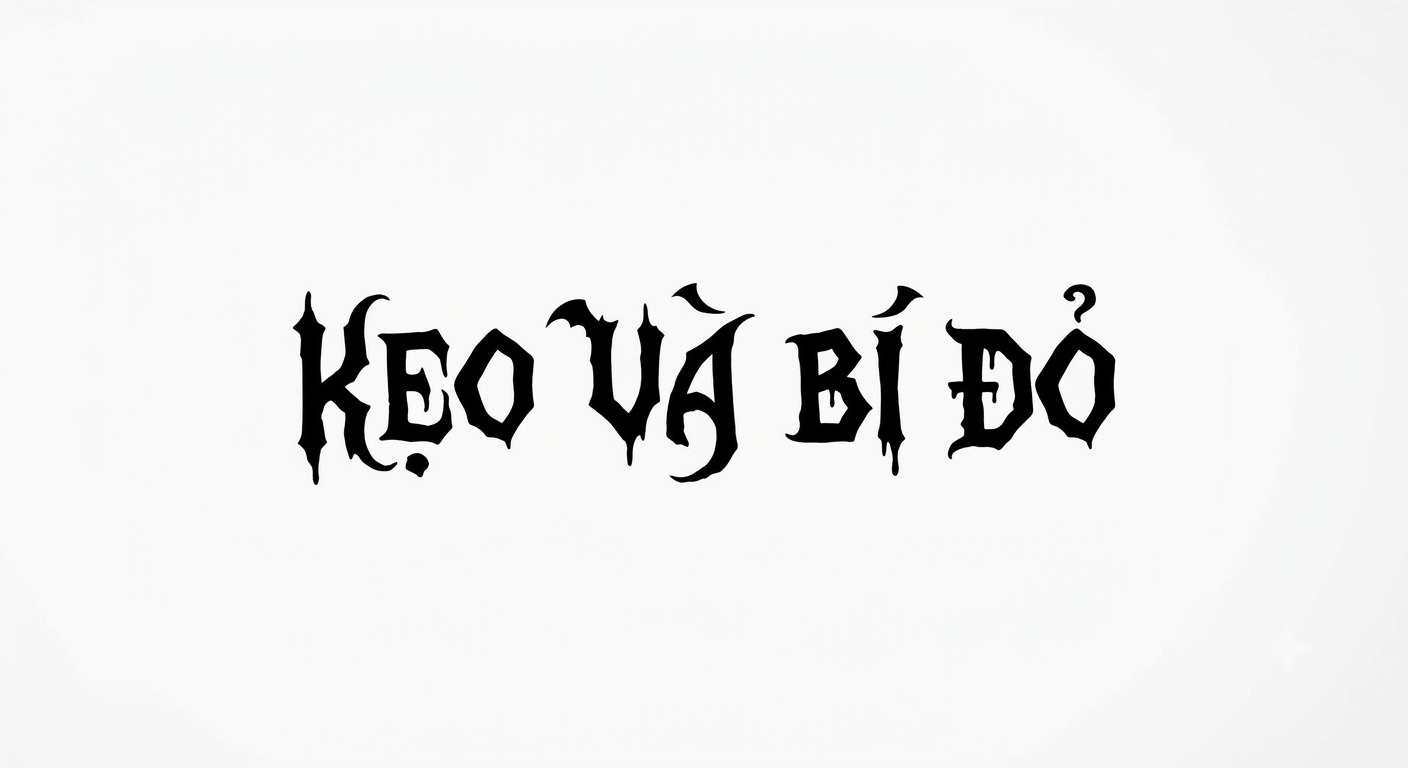
Font chữ Halloween là gì?
Font chữ Halloween là tập hợp các phông chữ mang phong cách kinh dị, rùng rợn, sắc nhọn hoặc mang đậm dấu ấn ma mị, lấy cảm hứng từ ngày lễ hội hóa trang cuối tháng 10. Đặc điểm của dòng phông này là các nét chữ có thêm chi tiết giỏ máu, xương xẩu, vết xước hoặc hình dạng kỳ quái, tạo cảm giác giật gân và tò mò cho người xem. Đây là lựa chọn quen thuộc cho thiết kế poster phim kinh dị, bao bì bánh kẹo sự kiện, nhãn hiệu đồ uống hoặc các ấn phẩm trang trí tiệc.
Ưu điểm nổi bật của bộ phông này là khả năng tạo không khí lễ hội ngay từ cái nhìn đầu tiên. Bộ phông hỗ trợ tốt cho việc làm nổi bật tiêu đề chính trong các bố cục sáng tạo. Bản Font chữ Halloween Việt hóa do In Viva cung cấp đã được căn chỉnh kerning cẩn thận, giúp các nhà thiết kế tự tin ứng dụng vào các dự án thương mại tại thị trường Việt Nam mà không lo lỗi hiển thị.
5 ứng dụng Font chữ Halloween Việt hóa trong thiết kế và in ấn
Nhờ phong cách chữ độc đáo, ma mị cùng các chi tiết gai góc đặc trưng, Font chữ Halloween Việt hóa được ứng dụng linh hoạt trên nhiều sản phẩm bao bì, quà tặng và ấn phẩm sự kiện theo chủ đề lễ hội:
- Thiết kế bao bì bánh kẹo và sản phẩm Halloween: Font Halloween phù hợp để thể hiện tên sản phẩm, logo hoặc slogan trên hộp bánh, túi kẹo, nhãn chai nước nhờ kiểu chữ phá cách, giúp sản phẩm tạo cảm giác thú vị và thu hút trẻ em trong mùa lễ hội.
- Sản xuất bộ quà tặng sự kiện hóa trang: Khi kết hợp cùng kỹ thuật in UV, ép kim hoặc khắc laser, Font Halloween giúp các sản phẩm như bình giữ nhiệt, sổ tay, hộp quà tạo điểm nhấn cá tính, phù hợp với các chương trình giải trí và sự kiện theo chủ đề.
- In ấn túi giấy thương hiệu giải trí: Logo sử dụng Font Halloween trên túi giấy Kraft, Ivory hoặc giấy mỹ thuật giúp các thương hiệu khu vui chơi, rạp phim, cửa hàng phụ kiện xây dựng hình ảnh nổi bật và khác biệt.
- Trang trí backdrop, poster và banner lễ hội: Với đường nét mạnh mẽ, Font Halloween phù hợp để thiết kế tiêu đề chương trình, khu vực check-in hoặc các ấn phẩm truyền thông trong sự kiện Halloween.
- Thiết kế tem nhãn decal sản phẩm: Các nét chữ dày và chi tiết đặc trưng giúp tên sản phẩm hiển thị rõ ràng trên nhãn dán chai lọ, hộp giấy hoặc bao bì quà tặng, tăng khả năng nhận diện khi trưng bày.
5 lưu ý khi sử dụng Font chữ Halloween Việt hóa
Để Font chữ Halloween Việt hóa giữ được vẻ độc đáo và đảm bảo độ sắc nét khi sản xuất thực tế, designer cần chú ý:
- Kiểm soát độ phức tạp của ký tự: Font Halloween thường có nhiều chi tiết trang trí, đường nét nhọn hoặc hiệu ứng rùng rợn. Khi sử dụng trên tem nhãn nhỏ, cần kiểm tra kích thước chữ để tránh mất chi tiết khi in.
- Tối ưu đường Path khi gia công dập nổi: Khi sử dụng Font Halloween làm logo trên hộp quà hoặc bao bì sự kiện, các điểm giao nhau và chi tiết gai góc trong file vector cần được xử lý kỹ để khuôn dập thể hiện rõ nét, hạn chế lỗi răng cưa.
- Điều chỉnh khoảng cách ký tự (Tracking): Các chữ có nhiều chi tiết trang trí cần được cân chỉnh khoảng cách hợp lý để tổng thể không bị rối mắt, đặc biệt khi sử dụng cho tên thương hiệu hoặc tiêu đề dài.
- Lựa chọn màu sắc phù hợp: Font Halloween thường kết hợp với các gam màu đặc trưng như đen, cam, tím hoặc đỏ. Khi in Offset hoặc in UV cần kiểm tra hệ màu CMYK để đảm bảo màu sắc đúng với thiết kế.
- Convert font trước khi gửi xưởng: Trước khi sản xuất, nên chuyển đổi Font Halloween thành dạng vector bằng lệnh Create Outlines để hạn chế lỗi thiếu font, sai ký tự hoặc thay đổi kiểu chữ khi mở file trên hệ thống khác.